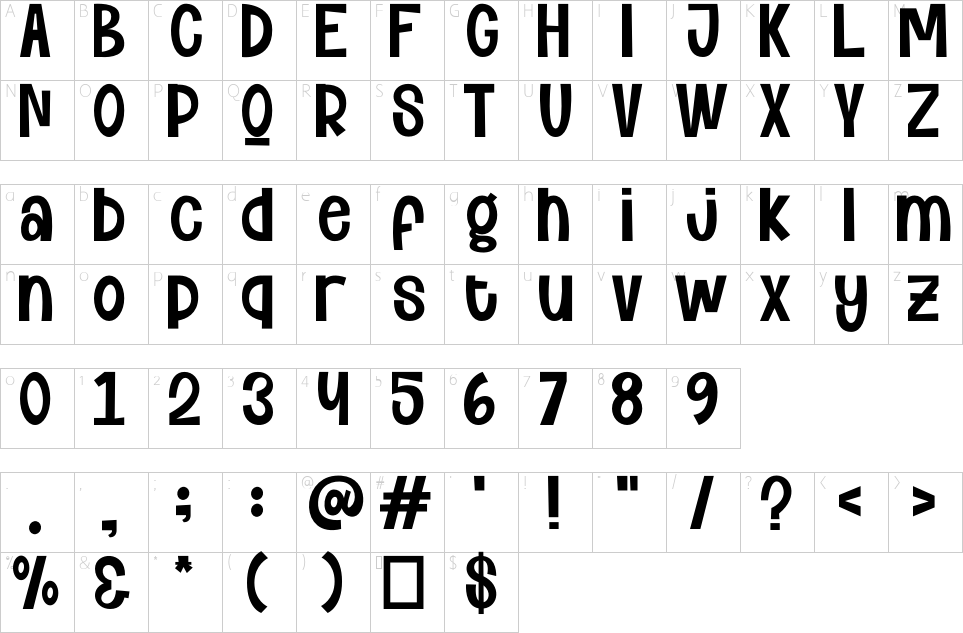
Descubra a sofisticação elegante da fonte Mogesty, uma escolha perfeita para projetos gráficos que exigem um toque de elegância. Desenvolvida pelo designer Jada Akbal, essa fonte está disponível gratuitamente para quem busca uma solução prática para seus trabalhos digitais. Mogesty é uma fonte de qualidade que combina elegância e elegância, ideal para criar design gráfico sofisticado. Recentemente, mais de 1.263 pessoas já tiveram a oportunidade de experimentar a Mogesty, demonstrando sua popularidade e valor. Seja para projetos de marketing, design gráfico ou qualquer outro tipo de projeto que você esteja lidando, a Mogesty é uma fonte que merece ser experimentada. Baixe hoje e adicione uma dose de sofisticação a seus projetos digitais.